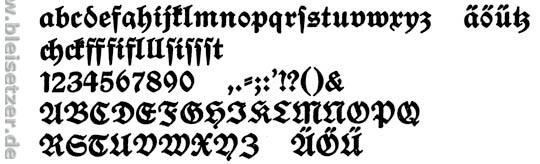
Bin ganz neu hier und durch Google zu euch gestoßen. Ich brauche dringend die Schrift, weiss aber leider nicht, wie sie heisst. Es geht um folgende:
Und zwar die im Logo. Flößerhof. Wäre wirklich über Hilfe dankbar!
Das sieht handgemacht aus (siehe ö/o-Formen, die ungewöhnlichen Unterlängen), ist aber bei dieser Auflösung schwierig zu sagen). Vielleicht musst Du tatsächlich etwas ähnliches zu Nachbauen suchen (z.B. bei Dieter Steffmann).
Ich glaube, daß wollte eigentlich 'mal so etwas werden - hat aber offensichtlich nicht ganz geklappt:
Gruppe Xc - Gebrochene Schriften - Schwabacher - Rediviva halbfett
Benjamin Krebs, Frankfurt am Main
Erstguß 1905
Franz Riedlinger
Eine Alte Schwabacher findest Du, wie hey schon schon schrieb, bei Steffmann.
Wenn es nur um den Schriftzug Flößerhof geht: Auf der Webseite läßt sich ein Flyer herunterladen, darauf ist das Logo als Vektorgrafik enthalten und man kann es sich da ja in bester Qualität rausholen.
Vielleicht kommt auch diese Fraktur „Scribbled Fraktur X-Heavy“ dem Gesuchten nahe
Sieht, im Vergleich zur Original Fetten Fraktur, ein bißchen arm aus, findest Du nicht? So "Ich möchte gern eine Fette Fraktur sein und nenne mich auch richtig cool 'X-Heavy'" :)
Es gibt in der Untergruppe Xd der Gebrochenen Schriften, den Frakturen, auch nur sehr selten ein Versal-J. Dieses hier hätte man vielleicht besser weggelassen.
Naja, aber der Original-Schriftzug ist ja nun auch nicht wirklich prickelnd.
Stimmt!
Bei vielen Schriften von M. Klein fehlen außerdem häufig die Ligaturen. Lediglich langes s und mit Glück ch und ck sind vorhanden. Aber dafür sind es ja auch Freefonts.
Die handgeschriebene Anmutung gefällt mir bei der „hippen“ Fraktur übrigens besser als bem Original, der Fetten Fraktur.